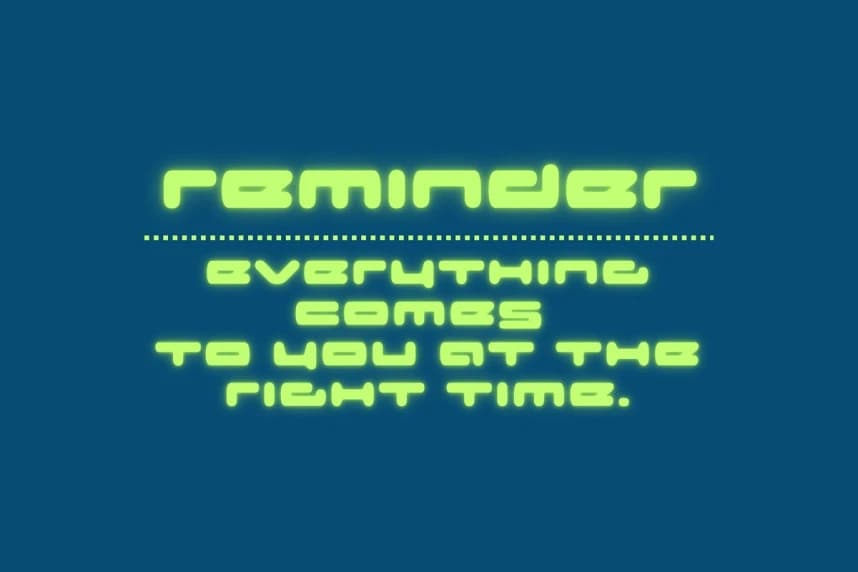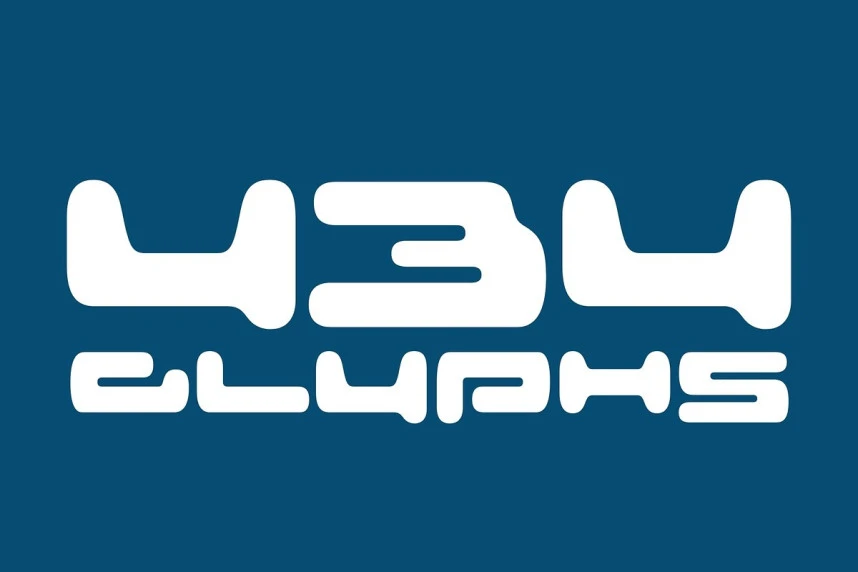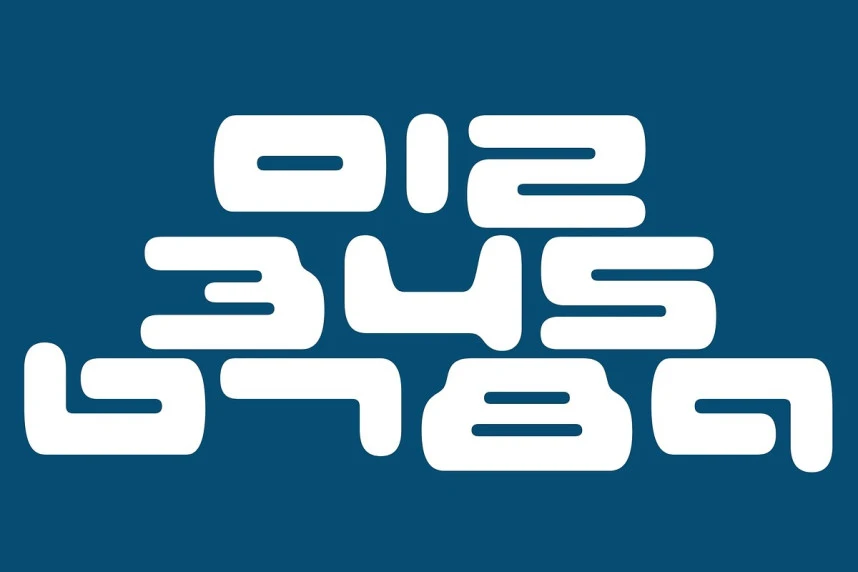
Cybernetik Fütüristik Yazı Tipi
Cybernetik Futuristic Font, Y2K döneminin cesur dijital estetiğinden ilham alan çığır açan bir font. Retro-fütüristik hisslerle dolu, keskin açılar ve zarif eğrilerle bu tipografi, 2000'lerin başı teknoloji iyimserliğinin özünü yakalarken modern sofistikasyonu da kucaklar.
Cybernetik Futuristic Font, Y2K döneminin cesur, dijital estetiğinden ilham alan son teknoloji bir yazı tipidir. Retro-fütüristik esintiler, keskin açılar ve zarif eğrilerle dolu olan bu yazı tipi, 2000'li yılların başındaki teknolojinin iyimserliğinin özünü yakalarken modern zarafeti de kucaklar.
Cybernetik Futuristic